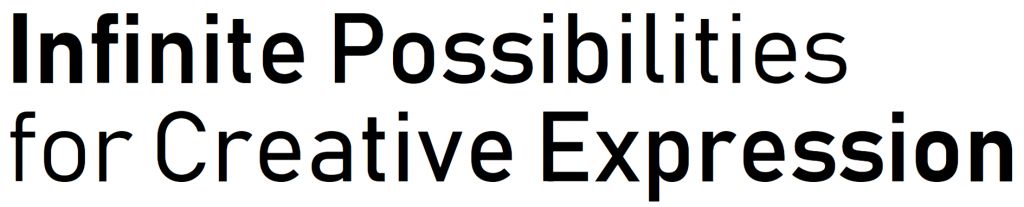
Zmienny font OpenType Microsoftu wróży koniec statycznego tekstu
Pamiętacie font parametryczny z repozytorium Google'a? Microsoft nie zostaje w tyle i w kompilacji Windows 10 Insider Preview Build 16273, dostępnej w Fast Ring i Skip Ahead, umieścił zmienny font OpenType o wdzięcznej nazwie Bahnschrift. Cyfrowe liternictwo znów zrobiło krok do przodu.
Specyfikacja zmiennych fontów została opracowany wspólnymi siłami przez firmy Microsoft, Google, Apple i Adobe jako część OpenType 1.8. Oficjalnie zaprezentowano ją niecały rok temu w Warszawie, podczas konferencji ATypI. W skrócie to jeden font, który zachowuje się jak tysiące różnych, pozwalając zmieniać odmianę, szerokość znaków i inne parametry bez ograniczeń, przy zachowaniu niewielkiego rozmiaru pliku. Projektant może zdecydować, które parametry pozwoli zmieniać, a które powinny być stałe dla jego kroju.
Dzięki temu fonty w końcu są gotowe na wymagania filozofii responsive design, choć z perspektywy Adobe dopiero teraz świat jest gotowy na zmienne fonty. Pomysł na litery, których parametry można zmieniać z zachowaniem kluczowych cech kroju pojawił się w tej firmie już w latach dziewięćdziesiątych. Wtedy jednak było za wcześnie, by proponowany standard się przyjął. Cieszy też to, że w przeciwieństwie do starszych fontów i metod wyświetlania, rozwijanych przez konkurencyjne firmy, OpenType jest owocem wspólnych starań o piękniejszy tekst.
Od strony użytkownika zmienne fonty dają ogromną elastyczność projektowania, bo przestajemy być ograniczeni do kilku typów (zwykle Light, Regular i Bold). Zmienny font pozwala na płynną zmianę odmiany (wagi, pochylenia) znaków, praktycznie bez ograniczeń.
Na marginesie warto dodać, że autorzy specyfikacji od razu zadbali o narzędzia pozwalające konwertować istniejące fonty do nowego standardu. Rok temu problemem był brak odpowiednich silników renderujących, zdolnych odpowiednio zinterpretować parametry i przenieść je na widoczne dla nas piksele. Dziś to już nieaktualne. Windows 10 Creators Update wprowadził wstępną obsługę zmiennych fontów w DirectWrite z obsługą najważniejszych parametrów. Wciąż trwają prace nad implementacją kolejnych, co widać w ostatniej kompilacji dla insiderów.
Z takimi fontami zyskujemy podwójnie. Na powyższym przykładzie znaki niezależnie od odmiany, mają identyczną szerokość, więc można dowolnie sterować „grubością linii”, a przy tym zachować wypracowany wcześniej układ tekstu. Jeśli tekst miałby zmieścić się w polu o innych proporcjach, można spokojnie zmienić wysokość glifów bez szkody dla szerokości i grubości linii. Dla projektantów to font idealny. Po drugie jeden plik jest w stanie zastąpić kilka statycznych fontów, co znacznie zmniejszy rozmiar projektów czy aplikacji. Na tym najwięcej zyskają strony internetowe.
Nazwa Bahnschrift zdradza korzenie kroju Microsoftu. To wariacja na temat standardu DIN, używanego na znakach drogowych w Niemczech i w kilku innych krajach europejskich. DIN cieszy się opinią czytelnego i niezawodnego, choć oczywiście kierowcy nieprzyzwyczajeni do niego mogą mieć inne zdanie.